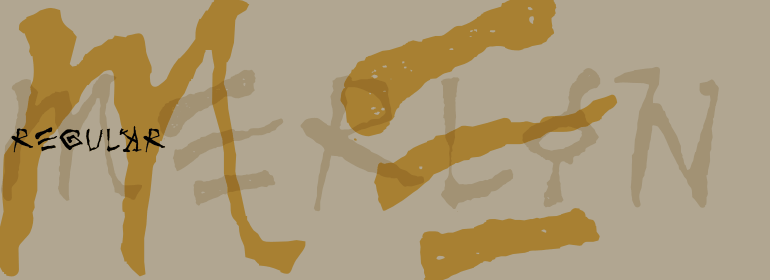
Merlin™
Merlin™,这款字体结构工整、笔画清晰,兼顾美观与易读性,适用于标题、正文、海报、包装、LOGO 等多种场景。字形优雅稳定,风格百搭耐看,适配日常排版与创意设计,让文字呈现更舒适、更具质感。Merlin™一笔一画,皆是细节,以均衡的比例、流畅的线条打造舒适视觉体验,字形端正大气,风格简约现代。无论是商业设计、品牌宣传还是日常排版,都能轻松驾驭,让文字更有格调与力量。Merlin™字体下载。